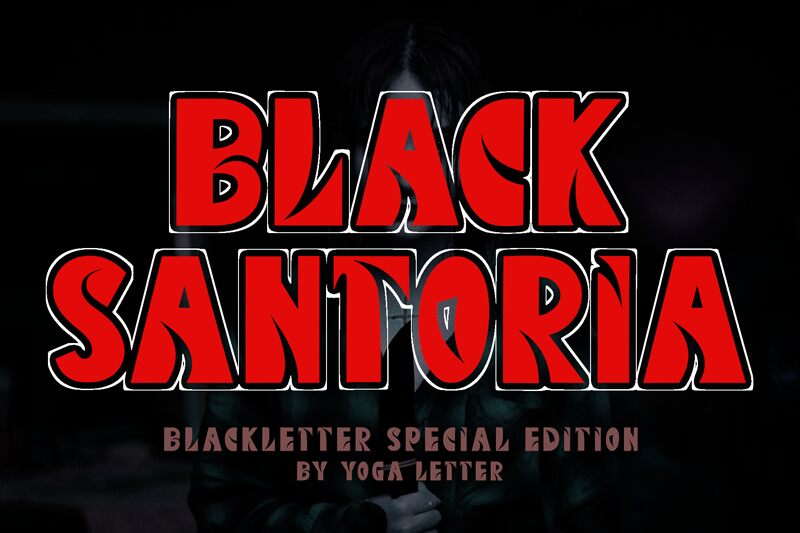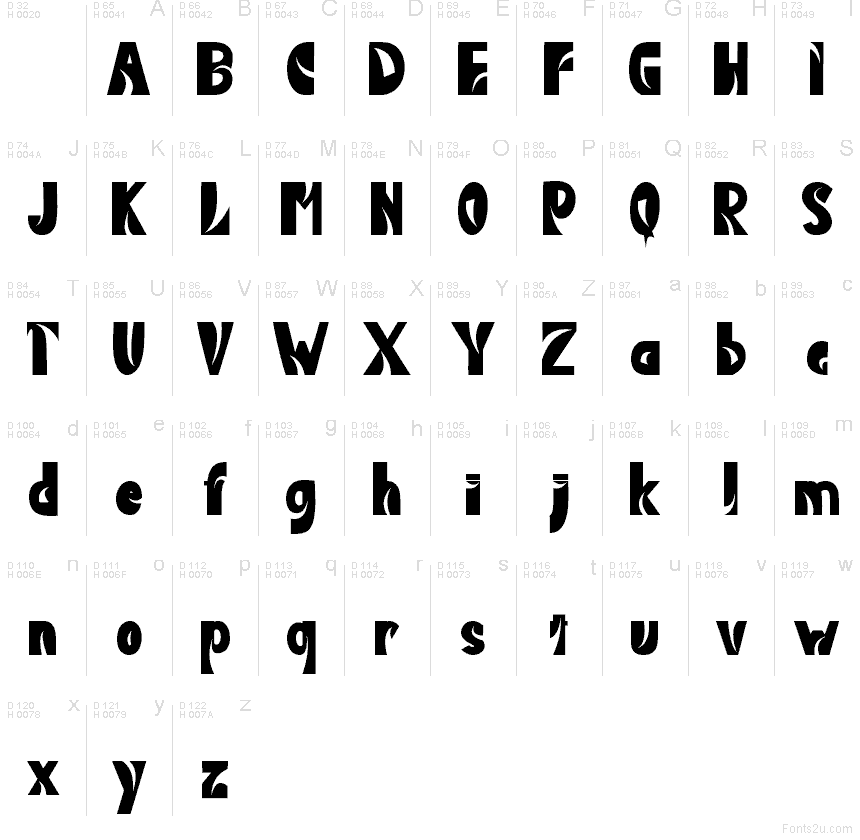
Black Santoria Demo
Black Santoria de Yoga Letter es una tipografía display gratuita con formas redondeadas, incisiones y una estructura robusta que aporta a cada letra un aspecto esculpido y estilo póster. Sus aperturas curvas recurrentes y ángulos suaves le confieren un carácter gráfico distintivo sin necesidad de ornamentos adicionales.
Black Santoria es una fuente gratuita excelente para titulares en carteles, logotipos, packaging, arte musical y gráficas de eventos donde el lettering es el protagonista del diseño. Sus formas contundentes y sus cortes interiores únicos también la hacen ideal para frases cortas, portadas y banners en redes sociales que busquen un acabado decorativo y lleno de fuerza.